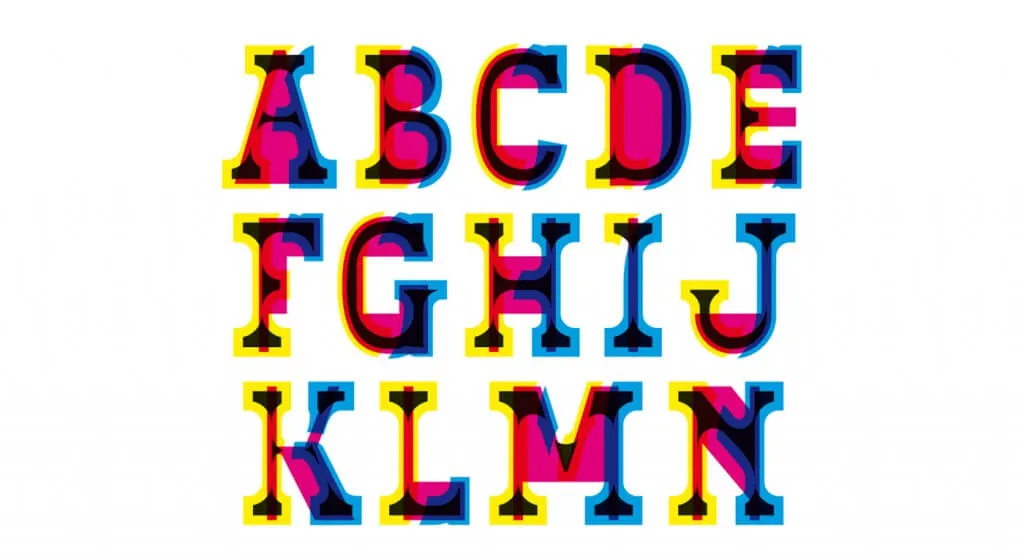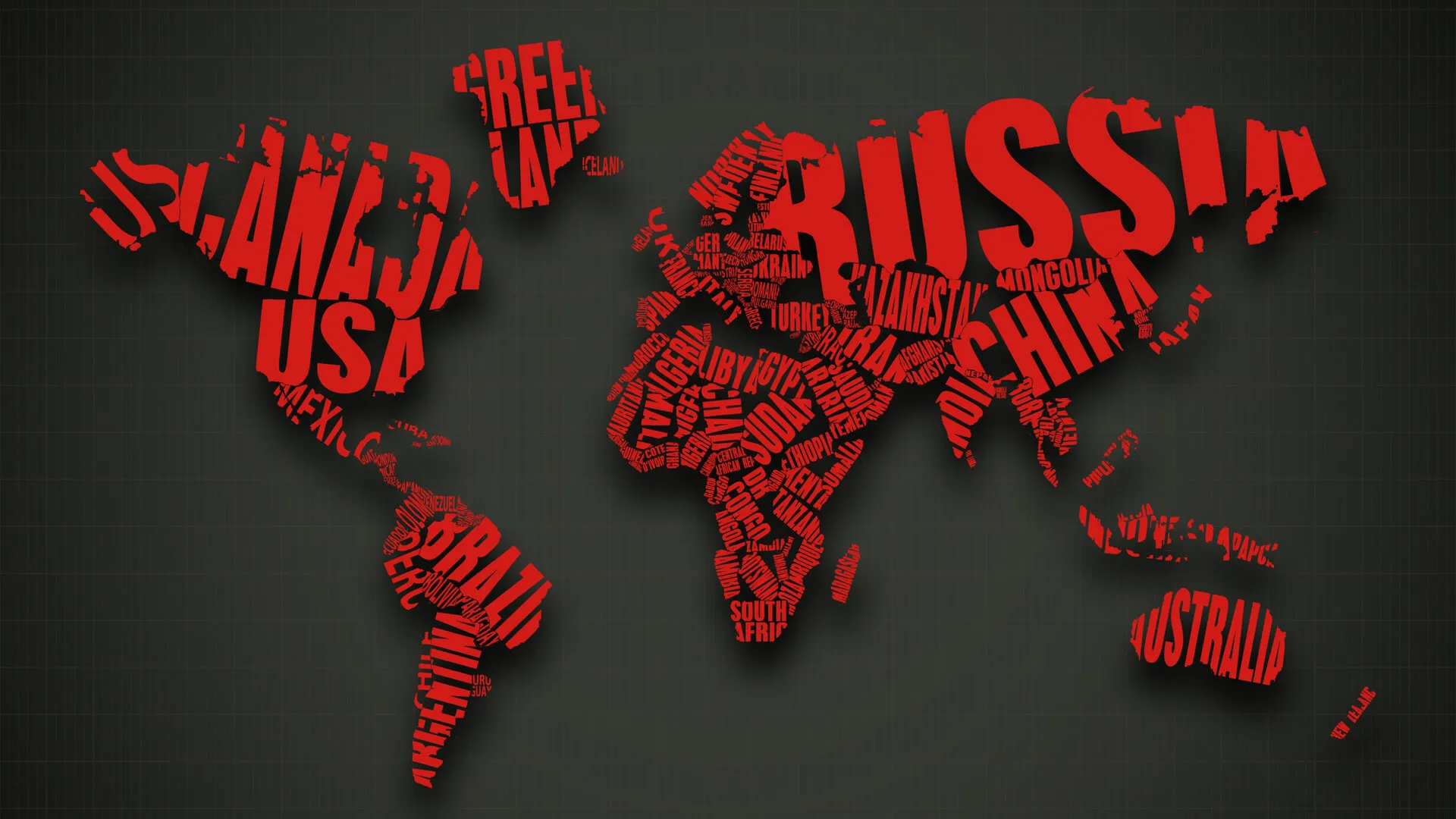
Tipografia com foco ao web design: fonte, tipo, tipologia e tipografia
Neste artigo sobre tipologia na web e seu uso em sites, algumas “questões tipográficas” serão apresentadas e, muito importante, reforçadas as diferenças entre termos comuns e frequentemente confundidos, como “tipologia”, “tipografia”, “tipo”, “fonte” e “fonte tipográfica”.
Considerações sobre a prática tipográfica na web
Os web sites, hot sites, mini sites, portais, sistemas web e softwares, campanhas online e o material encontrado na web, em geral, estão atualmente em uma fase de “amadurecimento”. As pessoas ainda estudam as melhores técnicas e possibilidades sobre o desenvolvimento para web e, devido a esta área do conhecimento ainda ser relativamente recente, ainda não se tem posicionamentos oficiais a respeito — na verdade, nem nas áreas de conhecimento e estudos “tradicionais” —, o que resultado em uma produção em massa de um material que poderia ter mais qualidade do que se vê.
A relativa facilidade de contato com o desenvolvimento web e, até certo ponto, ausência de obstáculos para se adentrar no ramo — fora o fato da disseminação de cursos do tipo “Web Design em 6 meses” e “Faculdade de web design”, que aparecem mais e mais —, todos estes figuram como incentivadores às pessoas.
Exemplo de tipo para web (tipografia web)
Num mundo perfeito não haveria tantos equívocos. A priori, pelo menos, é possível evitar alguns que são muito conhecidos, como é o caso da terminologia: tipologia e tipografia.
Tipologia ou Tipografia
Apesar de serem parecidos, os termos tipologia e tipografia são diferentes e, para não errar mais nunca, há que se dar a devida importância para isto. Aliás, não é apenas algum tipo de “capricho” de quem faz a confusão; a própria grafia e pronúncia são um pouco semelhantes e realmente podem causar confusão. Em um breve - mas muito bom - artigo sobre tipologia e tipografia, Sergio D Stefano, colunista do Webinsider, explica a diferença entre os termos:
Uma grande bobagem que tenho ouvido ao longo dos anos é a insistência no uso do termo tipologia a para classificação de tipos. Tipologia na verdade é um termo pertencente à taxionomia, a ciência das classificações, o estudo das características das diferenças entre objetos e seres vivos de toda espécie.
Nós temos a tipografia que, aí sim, é a arte e processo de criação de caracteres. A tipografia tem origem etimológica na implantação da impressão por tipos móveis na Europa, a partir do século XV. Portanto é a forma certa.
Na maioria das vezes pode parecer bobagem “ficar cismado” com falar uma palavra errada aqui, outra acolá, já que o que importa, mesmo, é entender sobre o assunto, em suas diversas nuances. Entretanto, ao utilizar um termo erroneamente estamos, em primeiro lugar, errando — e fazer isso, por exemplo, na presença de um cliente, pode ser muito desagradável — e, depois, transmitindo um conhecimento errado, propagando um equívoco que, se tivéssemos estudado um pouquinho mais a respeito, teríamos evitado.
Um profissional deve usar corretamente os termos de sua(s) área(s) de atuação. Não seria diferente para profissionais de web.
Então, para acabar de vez com este equívoco sobre tipologia e tipografia e, a partir de agora usar o termo correto, quando se está querendo referenciar a atividade de criação/estudo de tipos, usa-se o termo tipografia. Combinado?
Um pouco mais de informação sobre a Tipografia
Mais uma vez utilizando o bom conteúdo da Wikipédia, eis uma sucinta explicação sobre a Tipografia:
A tipografia (do grego typos — “forma” — e graphein — “escrita”) é a arte e o processo de criação na composição de um texto, física ou digitalmente. Assim como no design gráfico em geral, o objetivo principal da tipografia é dar ordem estrutural e forma à comunicação impressa. Tipografia também é um termo usado para a gráfica que usa uma prensa de tipos móveis.
Na maioria dos casos, uma composição tipográfica deve ser especialmente legível e visualmente envolvente, sem desconsiderar o contexto em que é lido e os objetivos da sua publicação. Em trabalhos de design gráfico experimental (ou de vanguarda) os objetivos formais extrapolam a funcionalidade do texto, portanto questões como legibilidade, nesses casos, podem acabar sendo relativas.
No uso da tipografia o interesse visual é realizado através da escolha adequada de fontes tipográficas, composição (ou layout) de texto, a sensibilidade para o tom do texto e a relação entre texto e os elementos gráficos na página. Todos esses fatores são combinados para que o layout final tenha uma “atmosfera” ou “ressonância” apropriada ao conteúdo abordado. No caso da mídia impressa, designers gráficos (ou seja, os tipógrafos) costumam se preocupar com a escolha do papel adequado, da tinta e dos métodos de impressão.
Apesar de estes conceitos e definições terem foco especialmente às mídias impressas, é perfeitamente possível e aceitável “adaptar” tudo e pensar sobre a tipografia com foco ao web design.
Conclusão
É importante, então, que se usem os termos corretos quando se estiver lidando com o estudo da tipografia e assuntos tipográficos, em geral, não fazendo confusão entre termos que, aparentemente, queiram dizer a mesma coisa. “Fonte” virou sinônimo de “Tipo” principalmente em função de traduções famosas equivocadas, mas o correto é “tipo de letra” ao invés de “tipo de fonte”.
Um profissional deve usar corretamente os termos de sua(s) área(s) de atuação. Não seria diferente para profissionais de web.